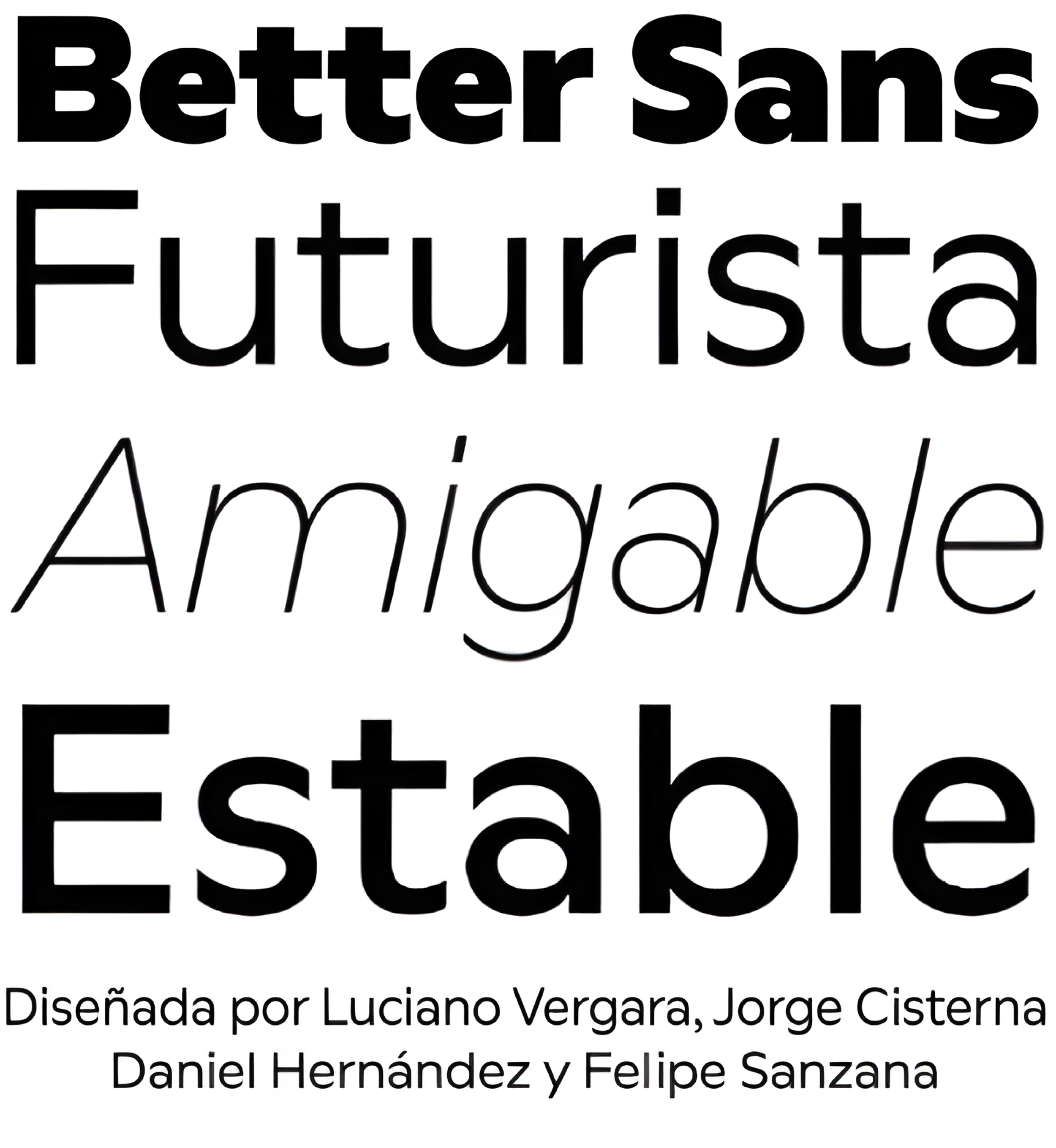
| Año | 2025 |
| Créditos | Luciano Vergara, Jorge Cisterna, Daniel Hernández, Felipe Sanzana |
| Descripción | Better Sans es como ese amigo de confianza que siempre hace brillar tus diseños. Sus componentes familiares hacen que sea fácil trabajar con ella y que la sientas como una compañera con la que has formado equipo en repetidas ocasiones. |
| Familia(s) | Better Sans |
| Estilos | 16 |
| Set | Especializado |
| Fundidora | Font Catalogue |